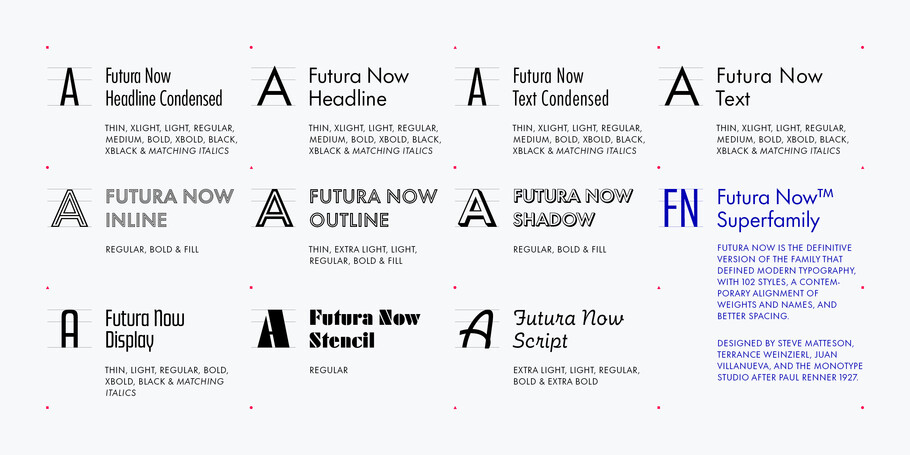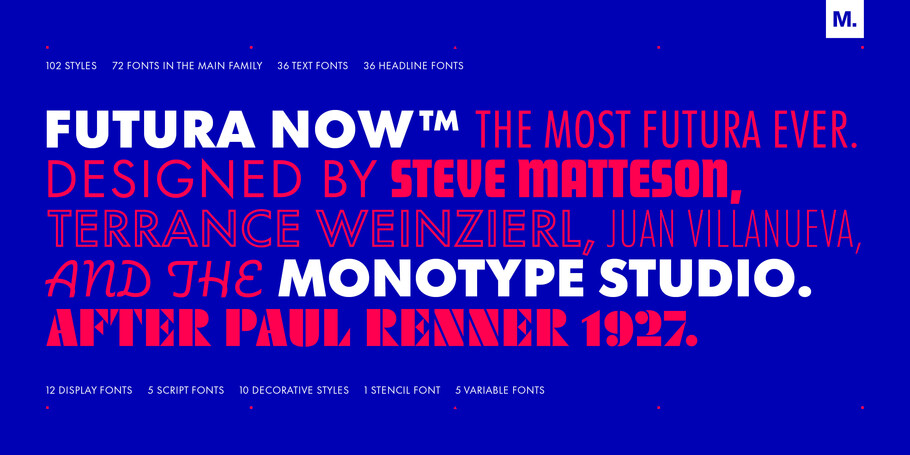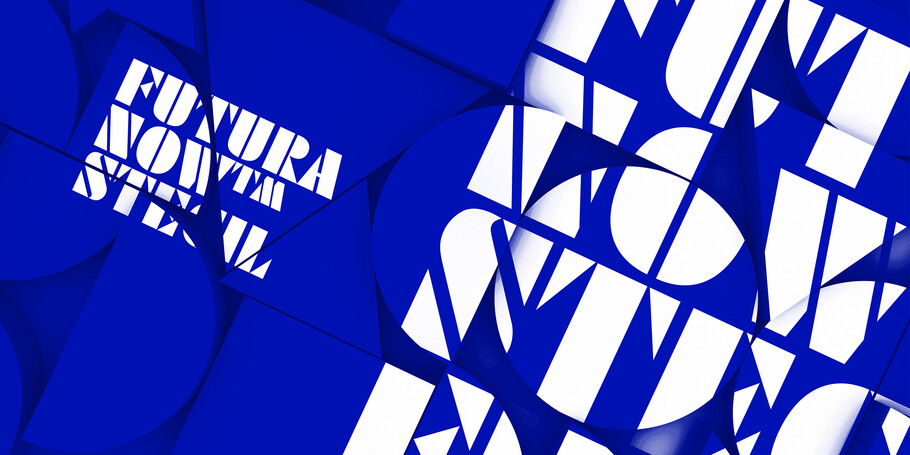
Futura® Now
Plus Futura que jamais.
Futura® Now, l’ultime version de la famille ayant donné à la typographie moderne sa définition, contient 102 styles (incluant des sous-familles Text généreuses en espace et Headline plus condensées). Son alignement contemporain des noms et des graisses apporte une expérience utilisateur améliorée. Elle est aussi disponible sous forme de police variable — déployant des styles illimités dans une empreinte digitale ordonnée.
Pendant presque 90 ans, la Futura de Paul Renner a été aussi populaire que polyvalente — des livres pour enfants aux magazines de mode en passant par la plaque commémorative sur la lune. Futura est tout simplement une icône typographique. Futura Now™ offre aux designers l’opportunité d’appréhender Futura avec un regard neuf. Cette version numérique est plus fidèle à la typographie originale que n’importe quelle autre version déjà expérimentée. « Elle insuffle une humanité essentielle dans le monde des géométriques sans serif », explique Steve Matteson, directeur de la création typographique chez Monotype, ayant dirigé l’équipe design. « Bien que réputée pour son modernisme par excellence, Futura Now™ est étonnamment chaleureuse. C’est parce qu’elle navigue habilement à la frontière entre une géométrie irréprochable et un humanisme chaleureux, qu’elle prend aussi bien sa place à la maison, aux côtés d’un arbre feuillu ou près d’une table en inox. »
Steve Matteson a conçu plus de 80 familles de caractères, y compris des polices pour les entreprises (comme Toyota, Microsoft et Google) et la bibliothèque de caractères Monotype, dont une douzaine de reprises des polices de Frederic Goudy.
En tant que designer typographique senior chez Monotype Studio, Terrance Weinzierl crée et modifie des polices pour la bibliothèque Monotype et diverses marques depuis 2008. En plus de travailler sur des projets personnalisés pour Microsoft, Google, Barnes & Noble, Domino’s et SAP, il a également créé des polices de caractères pour des jeux vidéo, des équipes sportives professionnelles et des constructeurs automobiles.
Juan Villanueva est designer typographique chez Monotype Studio à New York. Ses contributions à la bibliothèque de Monotype incluent des ensembles comme Walbaum et Sagrantino. Il a également contribué à des polices de caractères exclusives telles que Tencent Sans, Ricky Zoom, et plusieurs polices du projet Google Noto.